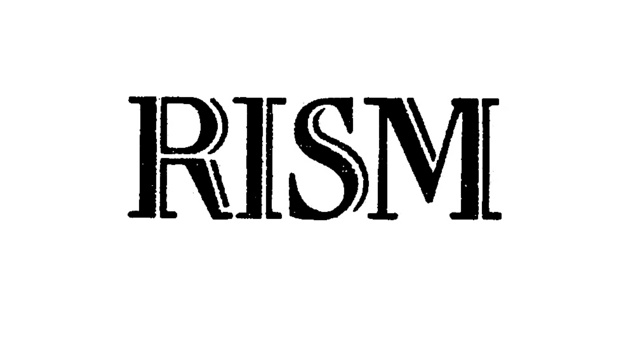
Dieses Logo kenne nur von den Einbänden des Repertoire International des Sources Musicales. Da der erste Band mit diesem Logo als Einbandprägung 1960 erschienen ist müsste eine Type auch davor veröffentlicht worden sein. Ich denke, dass dieses Logo gezeichnet ist, auch weil es in zwei Versionen existiert. Das von dir gezeigte Logo ist die vom G. Henle Verlag verwendete Form.
Dies ist die vom Bärenreiter Verlag verwendete Form.
Soweit ich sehe, unterscheiden sich die Formen auch von Band zu Band, was aber ein Ergebnis des Prägevorgangs sein kann. Eine Anfrage bei den Verlagen oder beim RISM könnte vielleicht Klarheit bringen, ob es sich um eine Type oder um eine Zeichnung handelt.